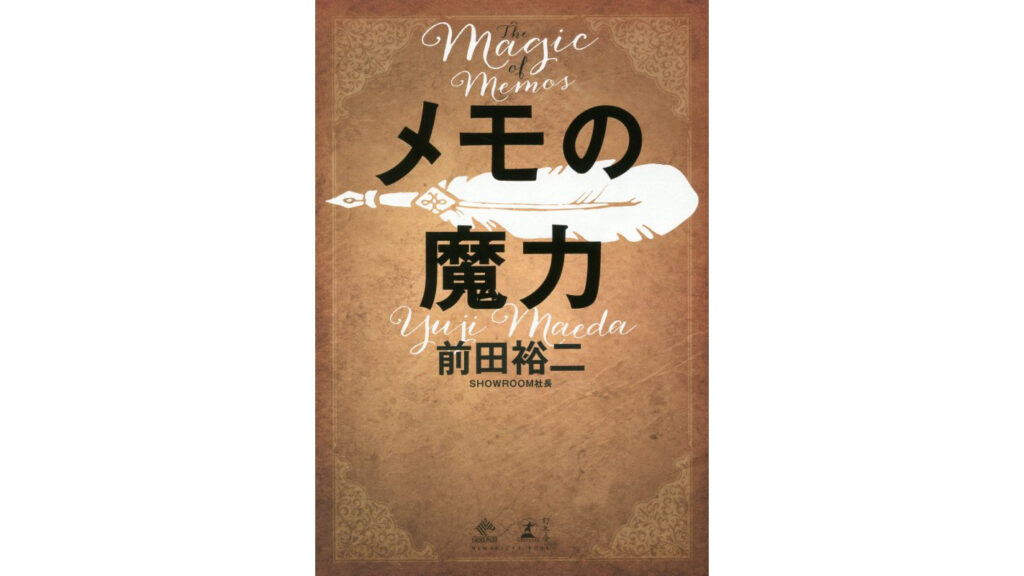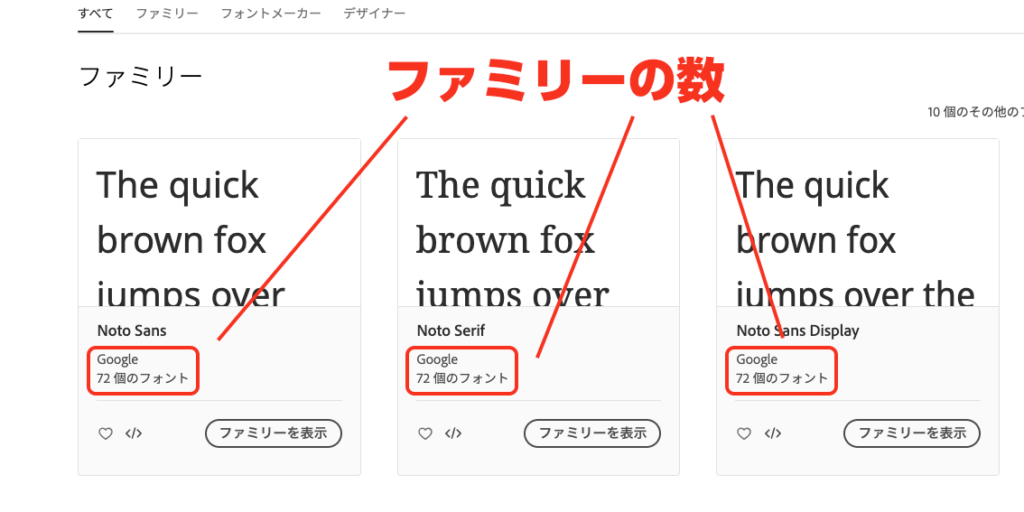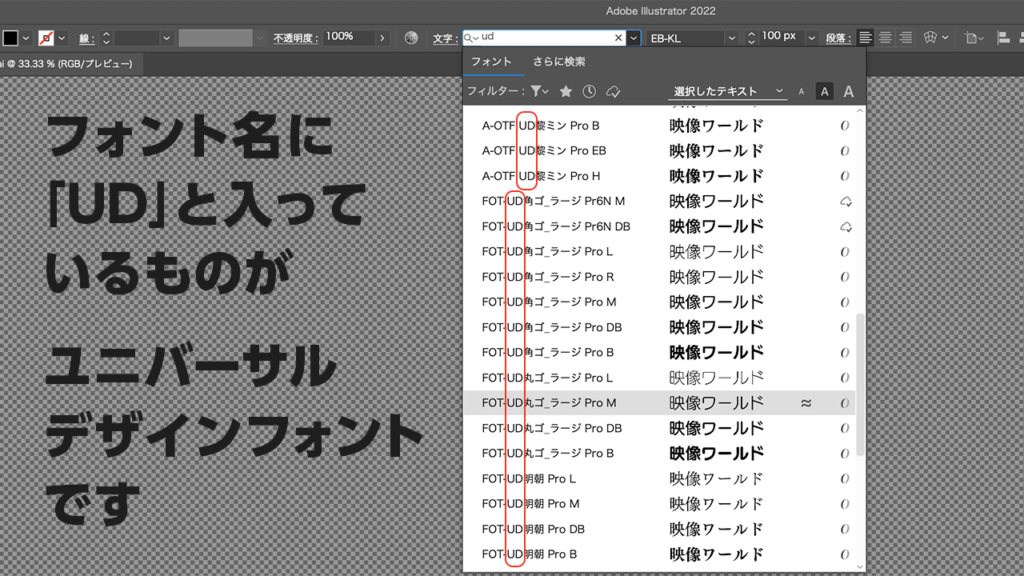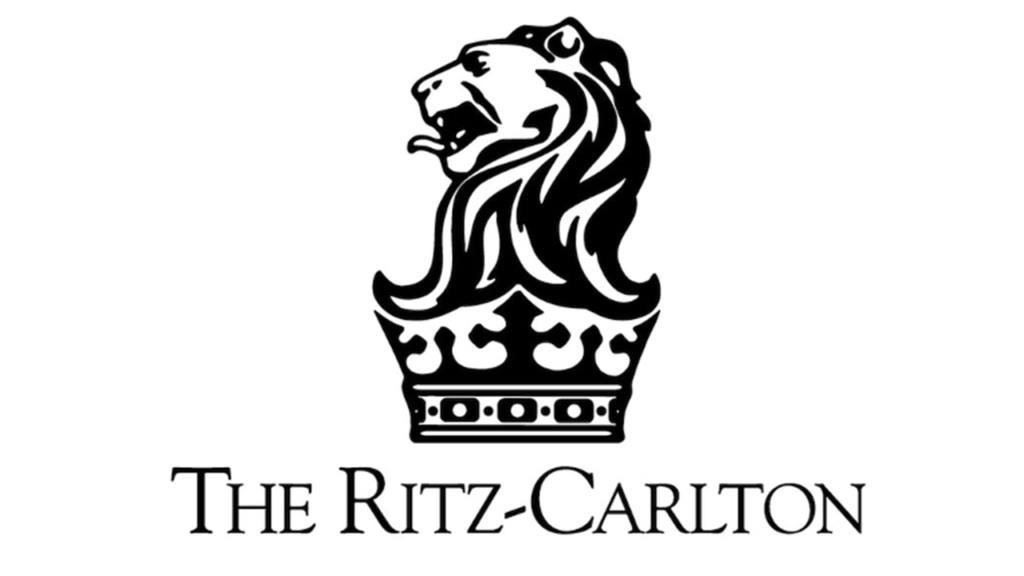
【モーショングラフィックス】失敗しないフォントの選び方
「モーショングラフィックのフォント選びが分からない」
「映像で使えるカッコいいフォント選びのコツを知りたい」」
「デザイン経験がない自分にはモーショングラフィックはできない?」
デザイン経験のない映像制作者や動画クリエイターには、
共通する疑問かと思います。
モーショングラフィックスの制作を始める方の多くは、
デザインについては全くの初めてという方も多いと思います。
実際にぼくもそうでした。
映像制作の勉強をし始めて、
デザインの勉強もしないいけないことを知った時は絶望を感じました。
理想をいえば、デザインもしっかりと勉強をした方が良いのですが、
正直映像制作の勉強もしないといけないので、
そこまでの時間もないと思います。
この記事では、
モーショングラフィックスを作りたい、
かつデザインのことを全く知らない人が、
ひとまず、すぐに使える最低限のデザインルールをまとめています。
こちらの記事を読んで頂くと、
フォントを失敗せずに選ぶ手順を理解することができます。
ぼく自身もデザイナーではなく、
映像制作から始め、これから紹介する方法や手順に従って、
フォント選びをすることが多いです。
そのため、実戦でも即使える内容になっています。
現役のデザイナーさんからすれば超超入門編くらいの内容ですので、
もしこちらの記事を読んで、本格的にデザインを学びたいと思った方は
さらにデザインの専門書で学習をすることをおすすめします。
【モーショングラフィックス】失敗しないフォントの選び方
そもそも、
『モーショングラフィックス』とは?
名前の通り、
『グラフィック』に『モーション』を
加えた映像のことです。
ですので、
モーショングラフィックスを制作するには、
グラフィックを作る技術やデザイン力が必要になります。
では、
グラフィックを制作(デザイン)するには、
どんな技術・スキルの要素が必要か?
主な要素はこちらです。
・レイアウト
・配色&配色レイアウト
・フォント選定
今回は、こちらの『フォント選定』についてを解説していきます。
デザインには一つの正解がなく、無限の組み合わせがあります。
フォント選びにおいても例外なく同じです。
そんな中、初心者がいきなりフォント選びをするのは
難易度がとても高いです。
本記事が、モーショングラフィックスのデザインで失敗しないための
一つの簡単な指標となれれば幸いです。
1.フォントの種類
フォントの種類は人によって分け方に多少の違いがありますが、
最低限、覚えておくべき種類を紹介します。
全くの初心者は、まず最初にこの4種類を覚えましょう。
「明朝体」
「ゴシック体」
「セリフ体」
「サンセリフ体」
以下に詳しく紹介していきます。
■和文フォント
明朝体・・・文字の先端にウロコが付いている書体です。
ゴシック体・・・直線的な書体です。
楷書体・・・一画一画書いた書体で、書道の手本としても使われている書体です。
そのほか・・・上記のどれでも該当しないその他の書体です。
■欧文フォント
セリフ体・・・文字の先端にセリフ(ウロコ)が付いている書体です。
サンセリフ体・・・直線的な書体です。
スクリプト体・・・筆記体の書体です。
そのほか・・・上記のどれでも該当しないその他の書体です。
フォントはどれでも良いという訳ではなく、
目的に沿ったものを適切に選ぶことが重要です。
さらに詳しく説明していきます。
2.フォントの選び方(6つのルール)
初心者におすすめしたい
フォント選びの6つのルールを紹介します。
①制作前に使うフォントを決めておく
特に初心者のころは、制作前に使うフォントを選んでおくことで、
ぶれずに統一感を持ったデザインにすることができます。
②使うフォントの種類を抑える
一つの映像に多くても3種類に抑えるようにしましょう。
最初の頃は2種類あれば十分です。
フォントのバリエーションを増やしたい時は、
ウェイトで調整するようにしましょう。
※ウェイトは文字の太さのバリーエーション
③言語に合ったフォントを選ぶ
日本語には日本語用のフォントを、
英語には英語用のフォントを選ぶようにしましょう。
↓↓文字の右側に表示されるテキストで言語の判別が可能です。
④目的に合わせたフォントを選ぶ
映像のテーマに合わせたフォントを選びましょう。
複数のフォントを使う際は、フォント同士の相性が大切です。
組合せについては、次章で触れています。
例1:洗練されたものや高級感を表現する時は、
セリフ体で細めのフォントを。
例2:子供向けがテーマであれば、
丸みのある可愛らしいフォントを。
イメージやテーマに合ったフォントが分からない時は、
現存する会社が持っているイメージとその会社ロゴで使用されているフォントを照らし合わせて参考にするのもおすすめです。またファッション雑誌や、書籍の表紙を参考にすると、どういうターゲットにはどんなフォントが良いのかを勉強することもできます。
フォントを配置する目的を考えるのも大切
文字を読ませたいのであれば、可読性・視認性が高いものを選ぶ。
アクセントとして入れたいのであれば、
デザインフォントを選ぶのもありです。
↓こちらの表紙で使われいてるスクリプト体のフォントは、
読ませるというよりも、デザインの意図で入れられています。
その他の考え方として
書体ができた背景でフォントを選ぶのも一つの方法です。
それぞれの書体には生まれた歴史があり、
その歴史を元にデザインと関連するものを選ぶこともあります。
例1:DINというフォントは1930年代にドイツの工業規格として作られた書体ですが、ドイツや、工業に関わるテーマがあればそれに沿って使用するのも一つの方法です。
例2:ヒラギノという書体は京都の柊野(ヒラギノ)に由来しますので、京都に関わるテーマや、京都の歴史に関連する際に使用するのも一つの方法です。
⑤メインフォントはウェイトの多いフォントを選ぶ
メインとなるフォントは太さの種類(ウェイト)が多いものを選びましょう。
ウェイトだけでもバリエーションを増やせることができることや、
同フォントであれば統一感を出すことができます。
メインとなるフォントに関しては、
4種類以上のウェイトがあるフォントを選ぶのがおすすめです。
⑥迷ったらユニバーサルデザイン(UD)フォントを使う
ユニバーサルデザイン(UD)フォントとは、
誰にとっても見やすくて読みやすく設計されたフォントのことです。
フォント名の中に「UD」と表記されているものが該当フォントです。
特にメインで使うフォントは可視性・可読性ともに重要ですので、
もし迷ったら「UD」のフォントを使うのもありです。
3.フォントの組み合わせ方
フォントは、ファッションと同じように、
使いたいものだけを自由に組み合わせるだけだと、
チグハグになってしまいます。
フォント同士の相性を考えることが非常に重要です。
初心者には、これが1番難しいです。
一文に和文・欧文を混同する際は、必ず同型のフォントを選びましょう。
■日本語の「明朝体」と英語の「セリフ体」
■日本語の「ゴシック体」と英語の「サンセリフ体」
フォントを組合せて使う際のおすすめ例
①高級感・モダンな印象(Bodoni + マティス)
②先進的な印象(Futura + 筑紫ゴシック)
③親みのあるワクワクする印象(adobe Handwriting + 筑紫A丸ゴシック)
↓デザイン初心者にフォント相性の良し悪しの判断は難しいので、
最初はこういった書籍を見ながら真似するのがおすすめです。
※大量のフォントの組合せ例とイメージが載っています。
4.文字組みについて
文字組みとは?
文字サイズや段落、字間・行間の調整をして文字を美しく見せることです。
フォントを使う時には、
フォントの文字組の調整を行いましょう。
4つの調整ポイント
①サイズ・・・単位は小さめに
強調する文字とそれ以外の文字とのメリハリを付ける
②改行・・・可読性・可視性・レイアウトを見ながら配置する
③字間・・・間隔を統一させる
④行間・・・文字サイズの1/2〜1/3くらいにするのがベター
字間の感覚を掴むなら、こちらで練習することもできます。
■Kern Type(字間トレーニング)
7.まとめ
1.フォントの種類
絶対に覚えておくべき4種はこちらです。
それぞれの特徴を理解しましょう。
「明朝体」
「ゴシック体」
「セリフ体」
「サンセリフ体」
2.フォント選びのの6つのルール
①制作前に使うフォントを決めておく
②使うフォントを2〜3種類に抑える
③言語に合ったフォントを選ぶ
④目的に合わせたフォントを選ぶ
⑤メインフォントはウェイト(4種以上)の多いフォントを選ぶ
⑥迷ったらユニバーサルデザイン(UD)フォントを使う
3.フォントの組み合わせ方
フォント同士の相性を考えることが非常に重要です。
↓デザイン初心者にフォント相性の良し悪しの判断は難しいので、
最初はこういった書籍を見ながら真似するのがおすすめです。
※大量のフォントの組合せ例とイメージが載っています。
4.文字組みについて
フォントを使う時には、
文字サイズや段落、字間・行間の調整をして
文字を美しく見せることが大切です。
■4つの調整ポイント
①サイズ・・・単位は小さく、強調する文字大きくする
②改行・・・可読性・可視性・レイアウトを見ながら配置する
③字間・・・間隔を統一させる
④行間・・・文字サイズの1/2〜1/3くらいにするのがベター
最後に
今回は、全くのデザインを知らない映像制作者向けに知っておくと
大失敗しない内容をまとめました。
これらのルールを守っていただくと、
初心者の方でもそれっぽくはなるかと思います。
ただ、デザインはデザイナーという専門職があるくらい深いので、
もっと極めたい方や、興味を持った方は専門書を読んで学習してみてください。